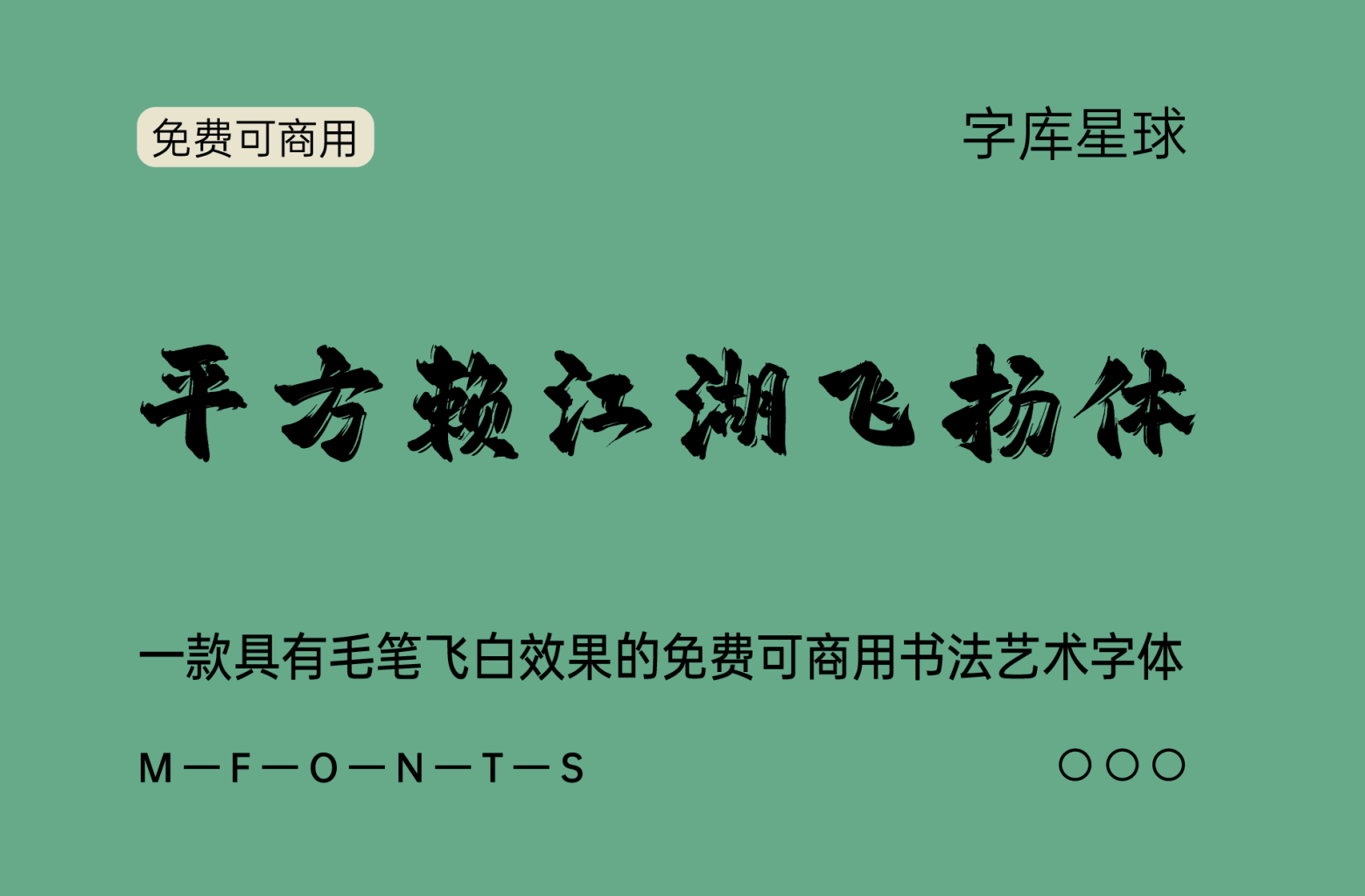
平方赖江湖飞扬体
这是一个具有毛笔飞白效果的书法艺术字体,它具有良好的视觉感受,适合用于艺术设计、平面宣传设计、网页设计、书法字帖等多个领域。此字体由平方字库出品。
平方赖江湖飞扬,如鹰展翅翱翔,书法如风,挥洒间奔腾。墨香漫卷,千里江湖,逐浪天际,岁月踏歌。笔下山河图,情意荡漾,豪情万丈,潇洒不羁。一纸书香,千古传扬,留下世间绝艳篇章,永载江湖传奇。
平方飞扬体的应用场景相当多样,尤其适合于那些需要展现中国传统风格的场合。例如,在书籍封面、海报、邀请函、品牌标志等设计中,平方飞扬体都能很好地传达出一种古典与现代相结合的美感。此外,它的粗犷线条和强烈的中国风情也常用于节日贺卡、文化活动的推广材料等。